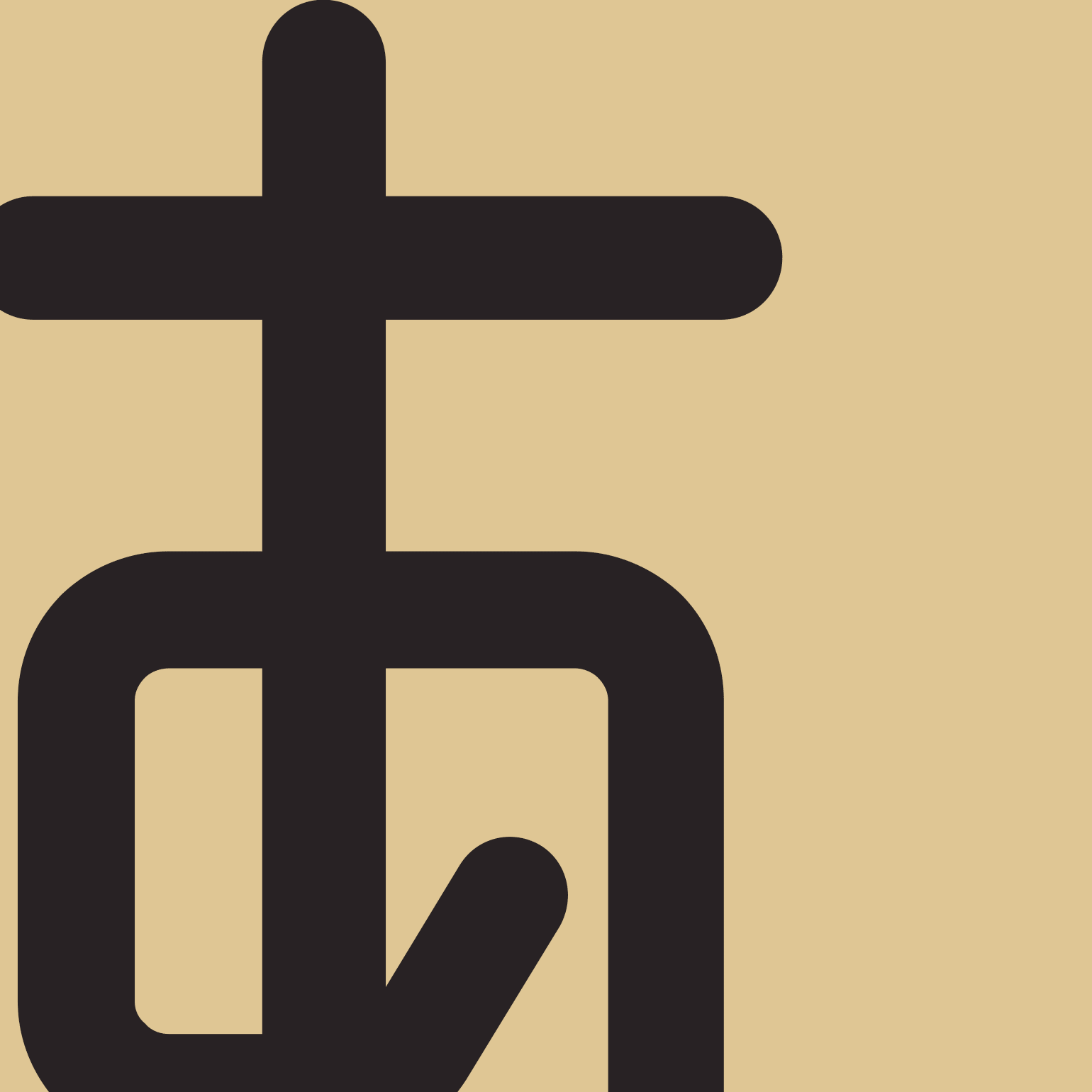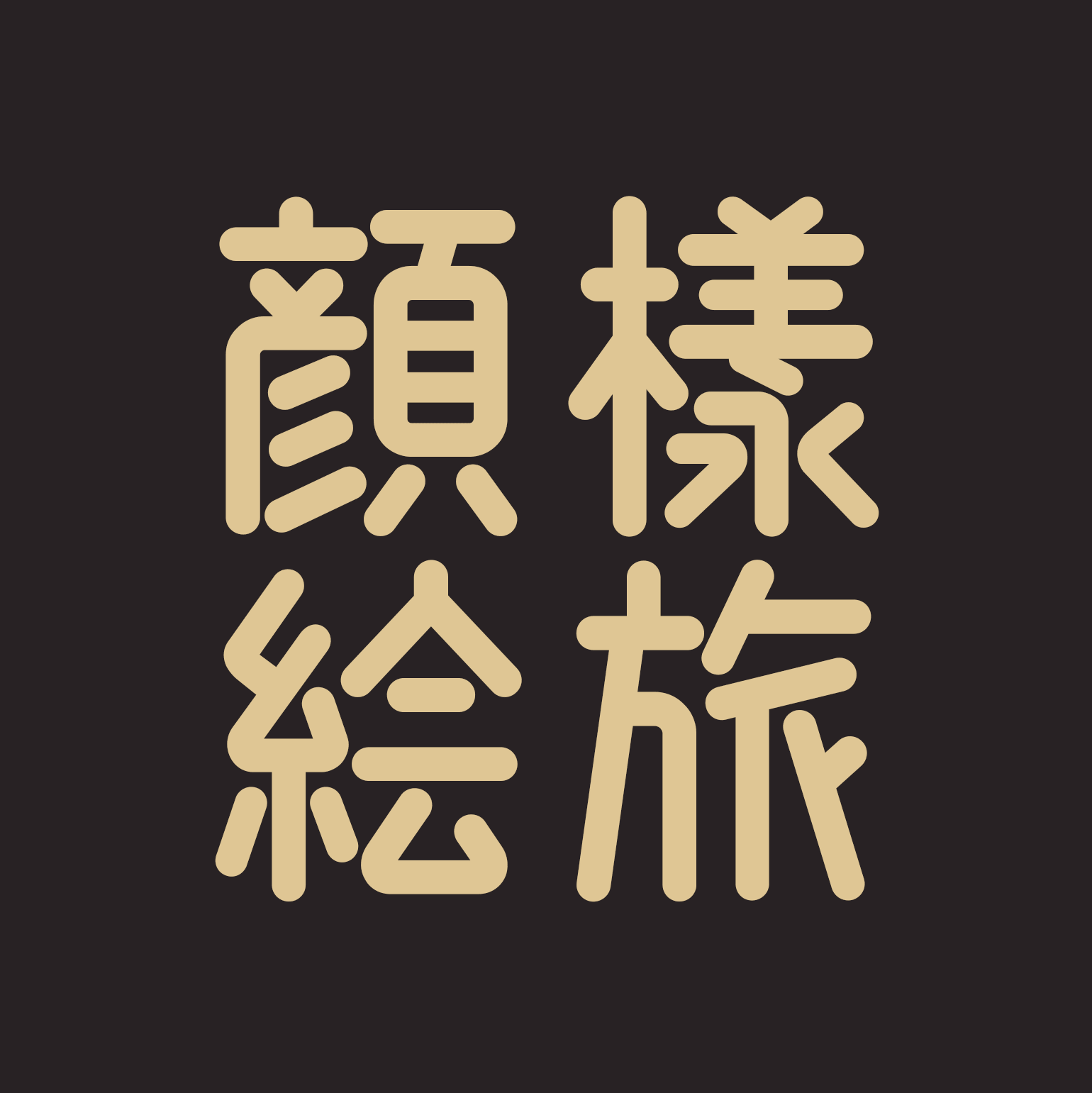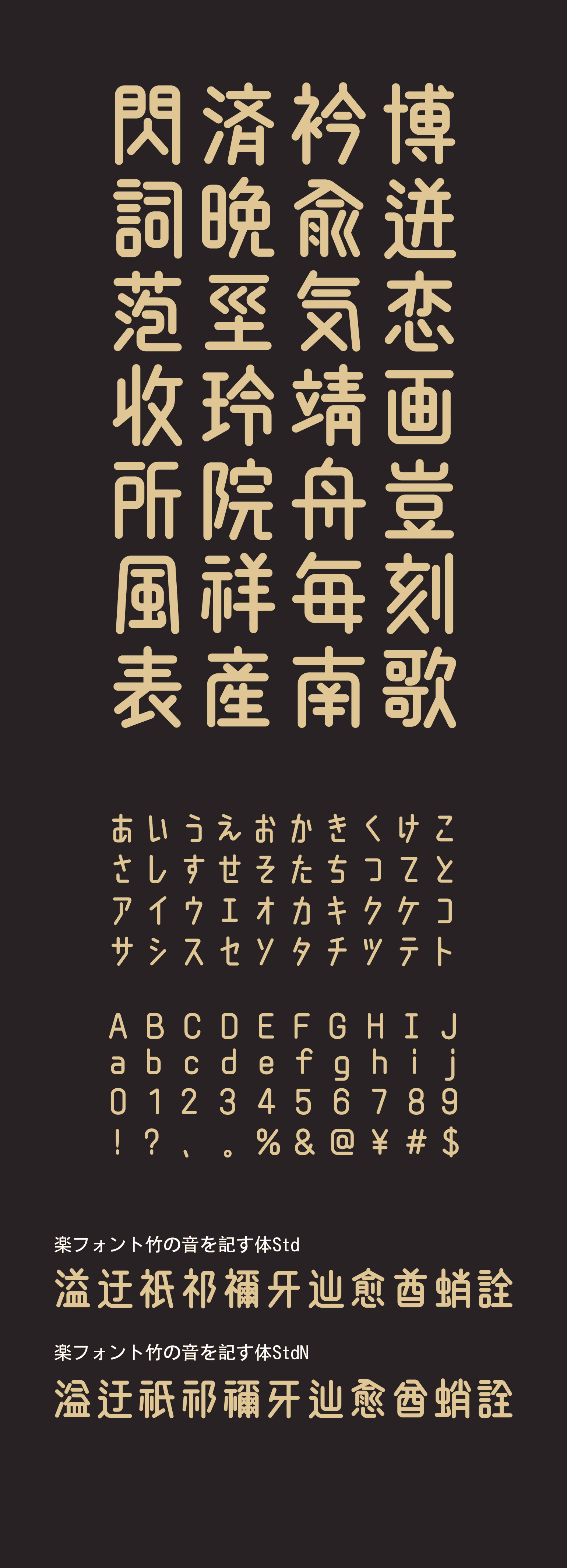
竹の音を記す体(たけのおとをしるすたい)
竹筆のように細くやわらかなストロークと、軽やかな
手書きのリズムが生み出す、やさしく親しみやすい表
情のフォントです。丸みのある形と心地よい余白が読
みやすさを高め、日常文やエッセイ風のレイアウト、
ヒーリング系、SNS など、柔らかい雰囲気を伝えたい
場面に最適です。